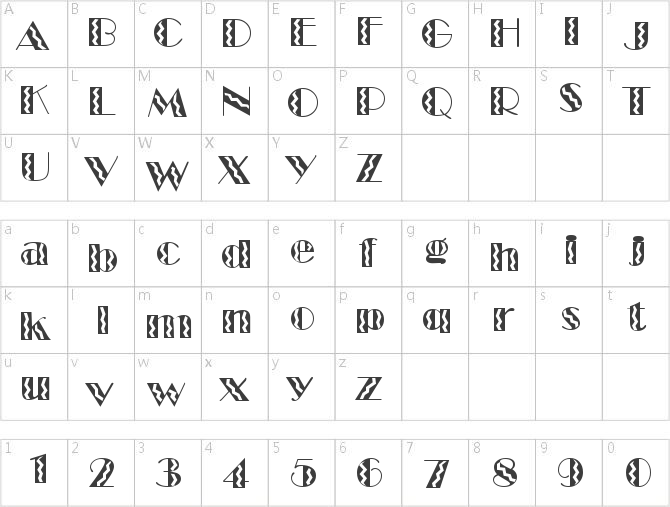
字體名稱: marquee
marqueeflashregular
marqueeflashregular介紹
marqueeflashregular字體字庫是一款讓人賞心悅目、百看不厭的英文字體,適合各類廣告和產品包裝設計應用,字體大小0.06MB,格式為ttf字體,上傳用戶是lvpyt,作者/版權方為未知